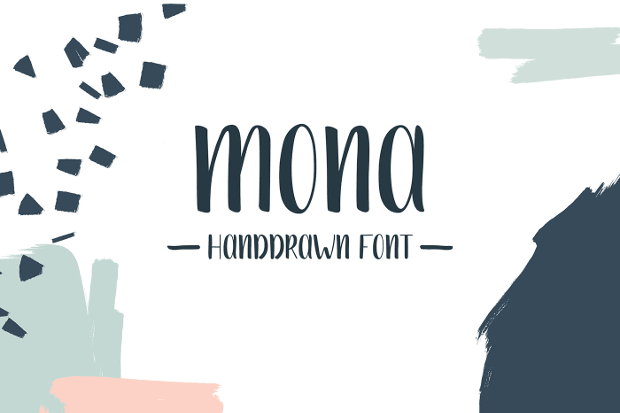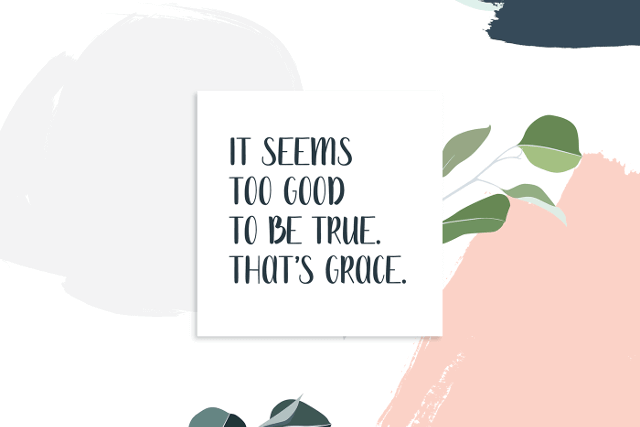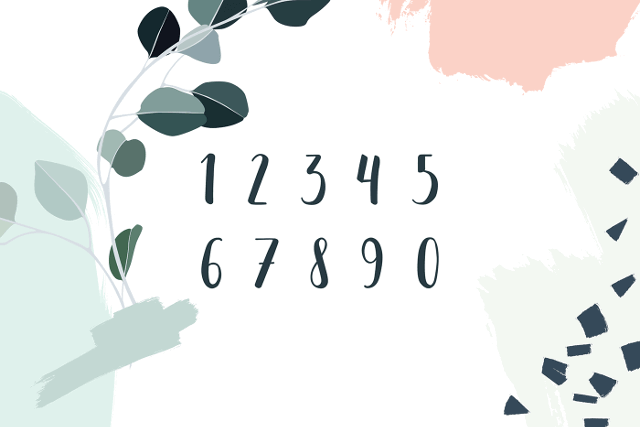
[系统字体] 刷子风格手写字体 MONA字体 资源介绍参数 资源类别: 精美字体 如遇问题: 联系客服/留言反馈 下载地址: 前往下载 精美字体 21年1月19日 编辑 前往下载 喵容发布2号 取消关注 关注 私信 资源名称 MONA 资源大小 154kb 资源格式 ttf、jpg 资源简介 Mona是一款手绘笔刷字体,具有对比鲜明的线条。非常适合徽标,海报和包装设计。 相关文章: [系统字体] 一款“狂野”风格字体系列:本文介绍的字体——Sonder是一款适用于徽标设计和大型游戏的字体。它有serif和sans-serif版本(即衬线字体和无衬线字体),同时它包括了两个样式(粗糙和常规)。该字体免费个人使用,商用需要购买哦! 下载 …... [系统字体] 复古脚本字体:本文介绍的是一款具有复古外观的脚本字体——Buffalo。它是品牌和标志设计的理想选择,有需要的朋友可以到文末下载哦! 下载权限查看 ¥ 免费下载 评论并刷新后下载 登录后下载 查看演示 {{attr.name}}: 您 …... [系统字体] 一款装饰性极强的字体——Moalang:今天分享的是一款装饰性非常强的一款字体——Moalang。它由印度尼西亚的字体设计师Agga Swist’blnk设计并且免费用于个人和商业用途! 喵容——Moalang字体1喵容——Moalang字体2 下载权限查看 ¥ 免费下载 …... [系统字体] 具有现代简约感的字体——axton:Axton是一款令人难以置信的圆润无衬线字体,具有现代和简约的感觉。它能让我们的作品脱颖而出。需要的朋友可以到文末进行下载哦! 下载权限查看 ¥ 免费下载 评论并刷新后下载 登录后下载 查看演示 {{attr. …... [系统字体] 现代简约字体 PEENU字体:资源名称 PEENU 资源大小 279kb 资源格式 ttf、png 资源简介 Peenu是一种免费的大写字体,由印度年轻UI和平面设计师Nitish Kumar设计和发布。Peenu受Sharp Paper Cuts的启发,它是海报,传单,电影片头等制 …... [系统字体]现代手写字体—GUTHERS:资源描述 字体 资源名称 现代手写字体—GUTHERS 资源格式 ttf 资源大小 385kb 资源简介 GUTHERS是一个单线脚本字体。印刷,网络,品牌,广告,杂志,产品,包装,标签等的完美选择。免费供个人使用! 喵容—— …... 喵容——MONA字体1喵容——MONA字体2 下载权限查看 ¥ 免费下载 评论并刷新后下载 登录后下载 查看演示 {{attr.name}}: 您当前的等级为 登录后免费下载登录 小黑屋反思中,不准下载! 评论后刷新页面下载评论 支付¥以后下载 请先登录 您今天的下载次数(次)用完了,请明天再来 支付积分以后下载立即支付 支付以后下载立即支付 您当前的用户组不允许下载升级会员 您已获得下载权限 您可以每天下载资源次,今日剩余次 声明:本文为原创作品,版权归作者所有。未经许可,不得转载或用于任何商业用途。如若本站内容侵犯了原著者的合法权益,可联系我们进行处理。 给TA打赏 共{{data.count}}人 人已打赏 MONA字体下载手写字条笔刷字体